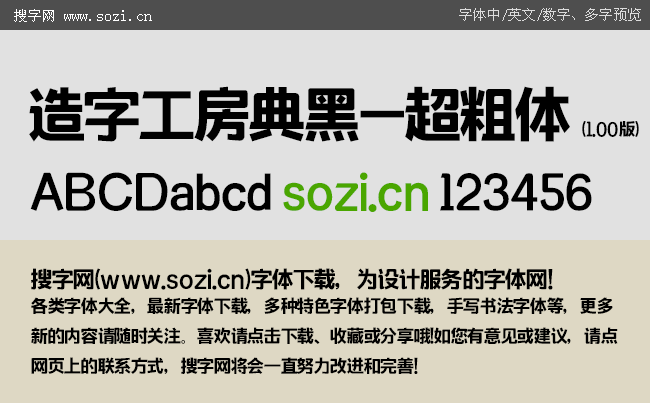
造字工房典黑超粗體
搜字網(wǎng)提供造字工房典黑超粗體中文藝術(shù)字體下載,造字工房典黑超粗體字形方正嚴(yán)謹(jǐn)、筆畫簡潔有力、中宮清晰,在黑體字形基礎(chǔ)之上巧妙創(chuàng)新,使其字形筆畫柔和而不失剛毅,風(fēng)格鮮明且極具易讀性。整體效果十分出色,可以應(yīng)用于廣告設(shè)計、名片設(shè)計、包裝印刷、產(chǎn)品設(shè)計等應(yīng)用。